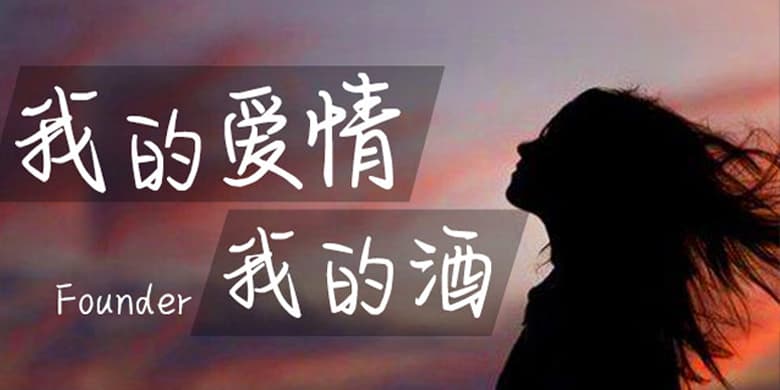
品牌:方正手迹设计师:余丹发行时间:2020字库编码:大陆简体(GB2312-80)分类:常规书写·硬笔字体属性:精品字
我的爱情我的酒是一款文艺风格的手写体。该字体中宫收紧,笔画舒展且多以曲线为主,整体给人一种流畅、有趣的感觉。适用于文艺类的书刊、品牌广告和产品包装设计,以及社交网络的个性化用字。